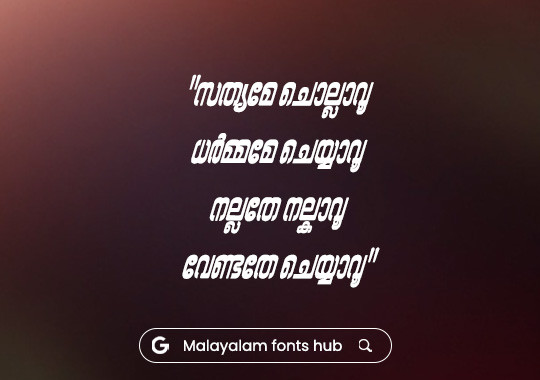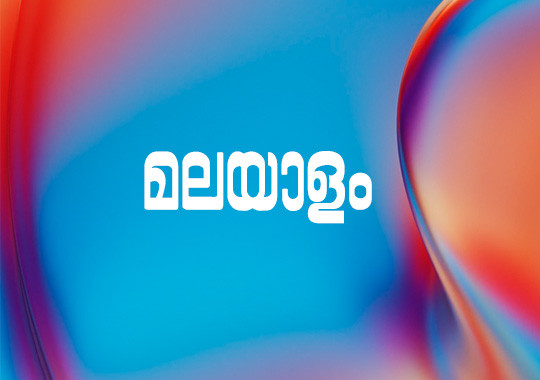
RIT Bahadur | Ornamental Traditional Malayalam Unicode Font – A Tribute to a Legend
മലയാള ചലച്ചിത്ര ലോകത്തെ ഇതിഹാസ നടൻ ബഹദൂറിനോടുള്ള (Bahadur) ആദരസൂചകമായി രചന ഇൻസ്റ്റിറ്റ്യൂട്ട് ഓഫ് ടൈപ്പോഗ്രാഫി (RIT) പുറത്തിറക്കിയ സുന്ദരമായ ഒരു ഓർണമെന്റൽ ഫോണ്ടാണ് RIT Bahadur.
പ്രചോദനവും ചരിത്രവും:
Artist Namboodiri's Design: 1978-ൽ ബഹദൂറിന്റെ അഭിനയ ജീവിതത്തിന്റെ 25-ാം വാർഷികത്തോടനുബന്ധിച്ച് പുറത്തിറക്കിയ സ്മരണികയുടെ കവർ ഡിസൈൻ ചെയ്തത് പ്രശസ്ത ചിത്രകാരൻ നമ്പൂതിരിയായിരുന്നു. ആ കവർ ഡിസൈനിലെ അക്ഷരരൂപങ്ങളിൽ നിന്നാണ് ഈ ഫോണ്ടിനാവശ്യമായ പ്രാഥമിക പ്രചോദനം ഉൾക്കൊണ്ടിട്ടുള്ളത്.
Design Geometry: RIT ഉറൂബ് (RIT Uroob) ഫോണ്ടിന്റെ ജ്യാമിതീയ ഘടനയെ അടിസ്ഥാനമാക്കിയാണ് ഈ ഫോണ്ട് നിർമ്മിച്ചിരിക്കുന്നത്.
Traditional Orthography: മലയാളത്തിന്റെ പരമ്പരാഗതമായ പഴയ ലിപി ശൈലിയിലാണ് ഈ യൂണിക്കോഡ് ഫോണ്ട് തയ്യാറാക്കിയിരിക്കുന്നത്.
പ്രത്യേകതകൾ:
Ornamental Style: ഡിസൈനോട് കൂടിയ അക്ഷരരൂപങ്ങൾ ആയതിനാൽ പുസ്തകങ്ങളുടെ തലക്കെട്ടുകൾക്കും സൈൻബോർഡുകൾക്കും ഇത് വളരെ അനുയോജ്യമാണ്.
Cultural Tribute: ഒരു വ്യക്തിയുടെ പൈതൃകത്തെയും നമ്പൂതിരിയെപ്പോലൊരു കലാകാരന്റെ ടാലന്റും ഒരേപോലെ അടയാളപ്പെടുത്തുന്ന ഡിസൈൻ.